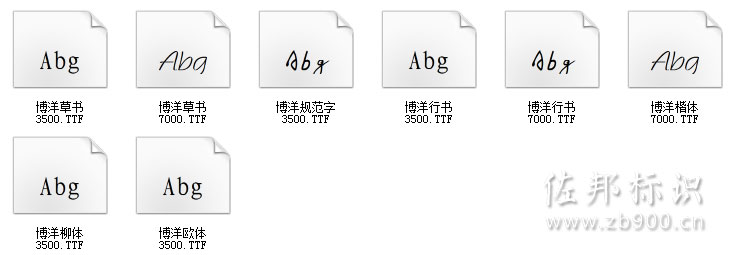
博洋字体是一种比较个性化的字体,特别是在美术设计创作、平面设计等方面具有较高的知名度。该公司主要产品以模拟真实的毛笔手迹为主打方向,融合了中国古老的汉字文化和现代计算机技术,可运行于Windows/98/me/2000/XP/win7和MACOS操作系统上,字体完全按照中国的GB2312-80标准。博洋字体,特别是博洋行书字体,在电脑上的效果和手工书写一样逼真,很有一种手抄体的亲切感和真实感。